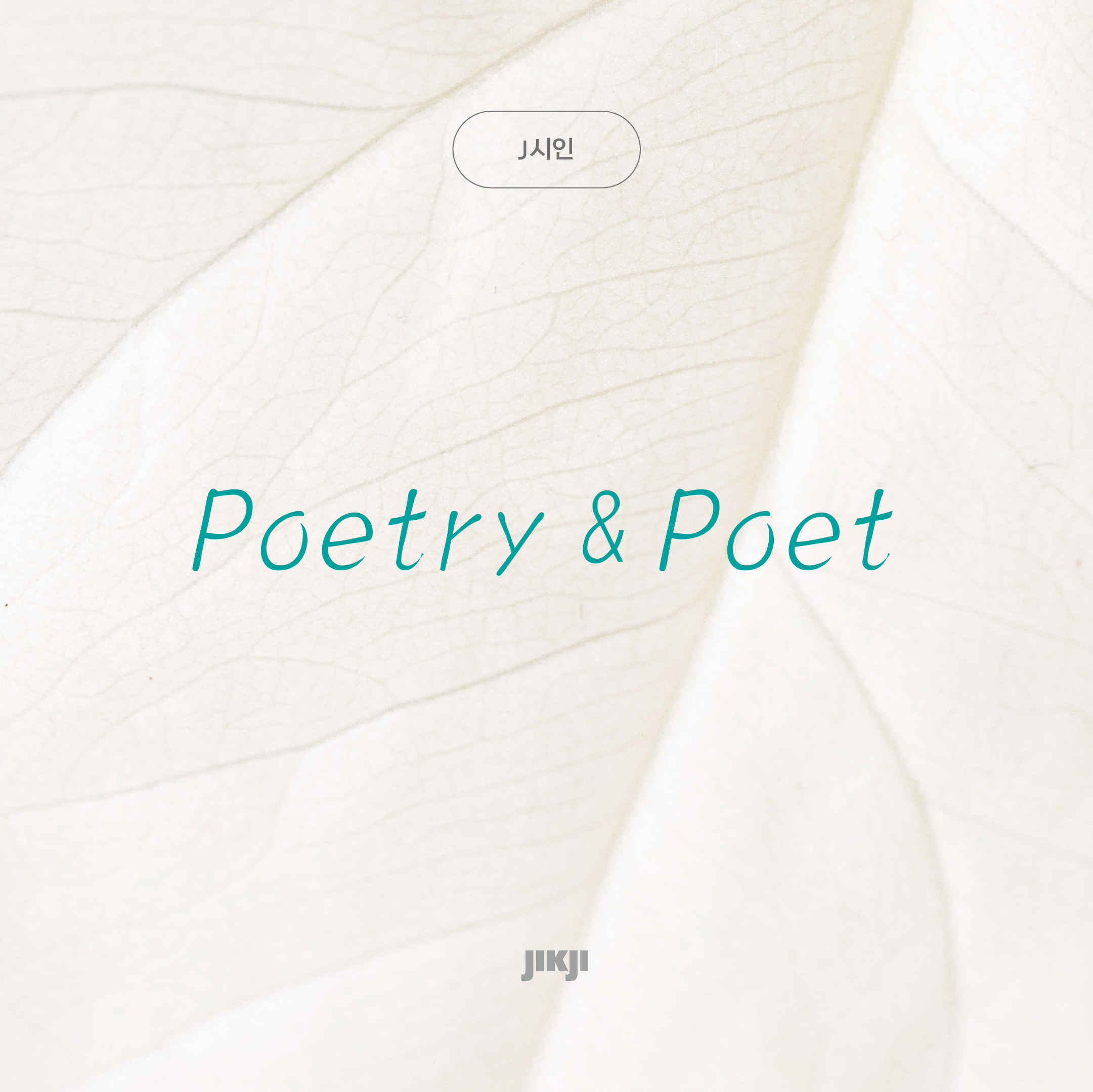
직지손글씨
손글씨가 주는 친근함과 개성이 돋보이는 서체이다.
J시인은 끝이 뾰족한 펜촉의 질감을 살리고 영문의 이탤릭처럼 오른쪽으로 기울어진 것이 특징인 필기체입니다. 빠르게 써 내려간 듯한 필기감과 손의 힘의 변화로 생기는 강약 변화가 생동감을 더하며, 전체적으로 강한 개성과 역동적인 인상을 줍니다. 영문의 이탤릭체처럼 자연스러운 흐름과 기울임을 통해 텍스트에 활기를 불어넣으며, 메모, 타이틀, 감성 메시지, 아트웍 등에 잘 어울립니다.